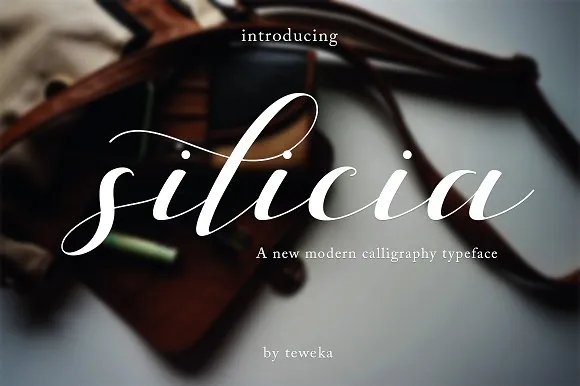
Silicia Script Font
Introduzimos Silicia Script Font! Desenhada por Teweka, esta é uma font premium disponível para download gratuito no CreativeMarket hoje. O estilo elegante e contemporâneo desta font, com seus caracteres feitos à mão e sua linha de baixo dançante, será perfeito para o seu próximo projeto. Adaptable tanto para cartas de cumprimento quanto para materiais de marca, Silicia Script é uma escolha ótima para impressão de business cards, criação de citações, publicações em cartazes e muito mais. Seu estilo fresco e moderno certamente enriquecerá seus projetos digitais ou impressos!